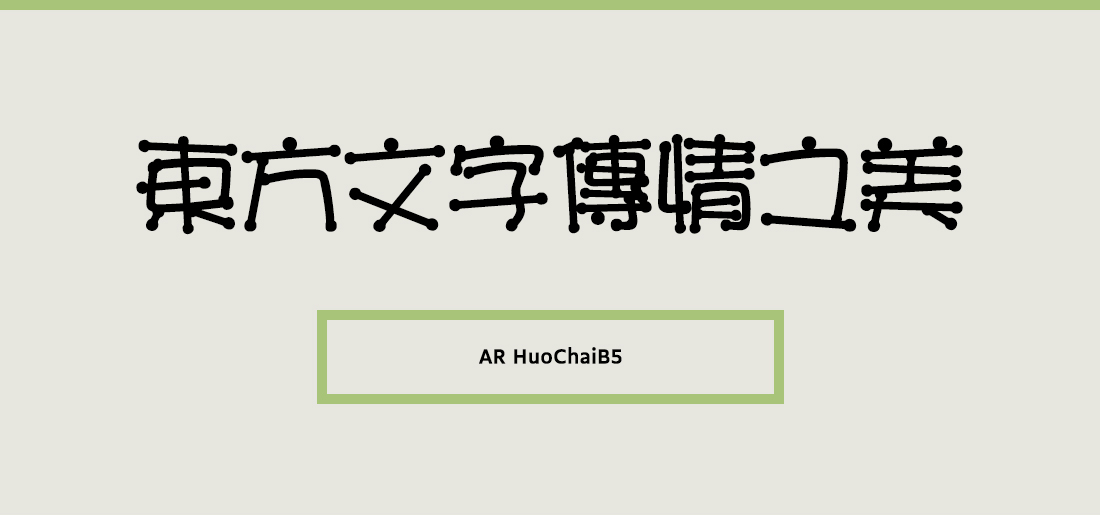
AR HuoChaiB5
HuochaiB5는 어린아이를 연상시키는 폰트이다.POP4를 연상시키는 장식적인 특징을 포인트로 갖고 있으면서도 읽기에는 큰 무리가 없다.폰트명 뒤에 붙은 B5라는 표기는 번체의 문자코드인 BIG5를 뜻한다. 번체란 중국을 제외한 대만, 홍콩, 마카오 등의 중화권 국가에서 사용하는 전통적인 모양의 한자다. 중국에서 사용하는 간체(GB)와는 달라 잘못 적용할 경우 글립이 제대로 표기되지 않거나 다른 글립으로 표기되는 문제가 발생할 수 있다.